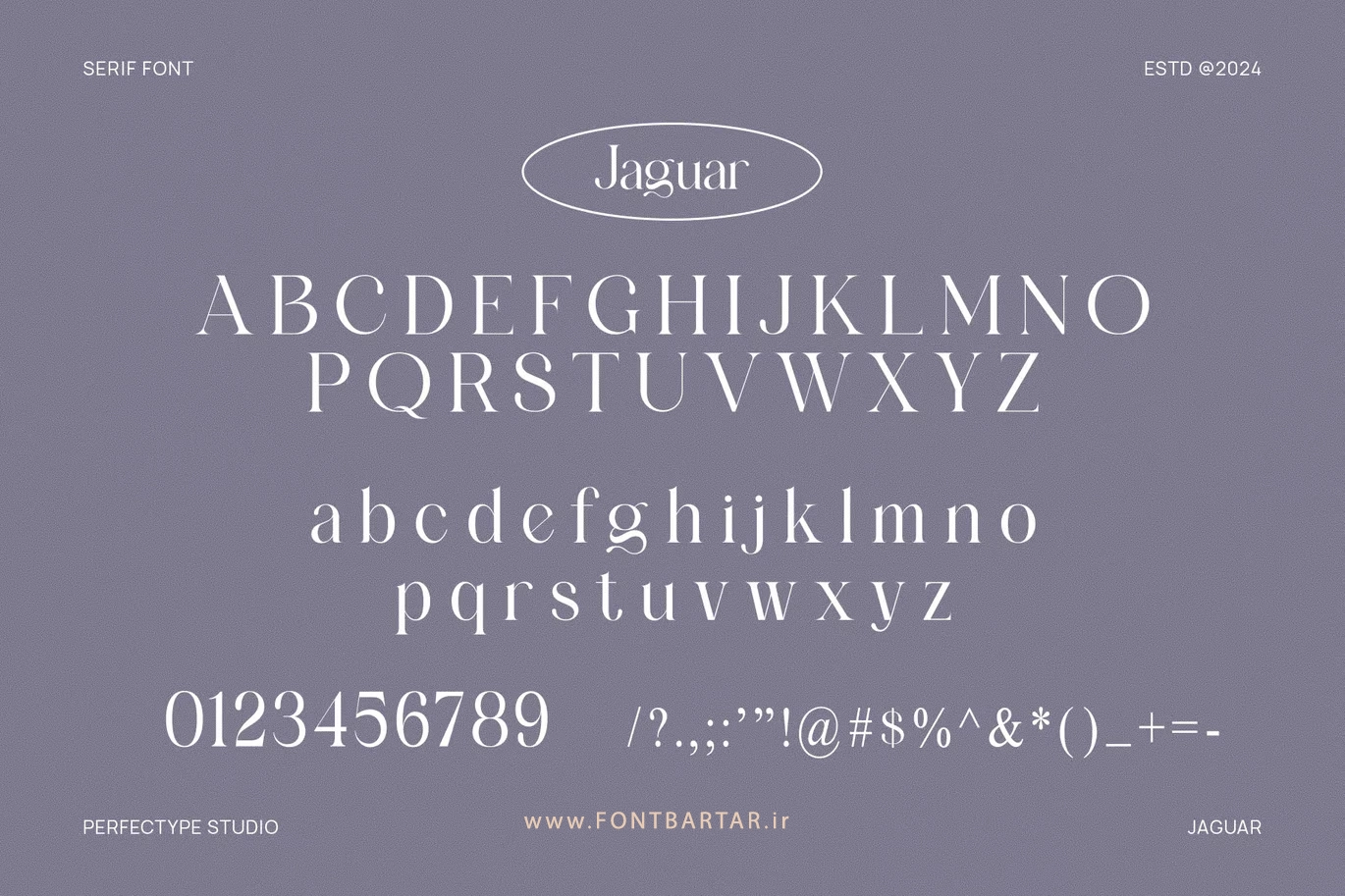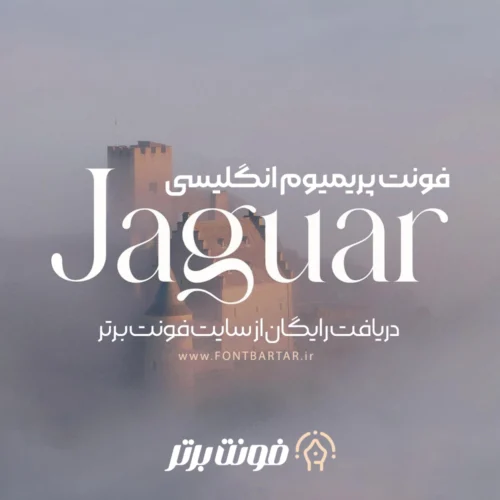
فونت پریمیوم انگلیسی Jaguar یکی از فونتهای خاص و پرطرفدار برای طراحیهای مدرن و لوکس است. این فونت با ترکیب خطوط نرم و انحناهای ظریف، حس شیک و مینیمال را به آثار شما میبخشد. فونت پریمیوم Jaguar اگر به دنبال فونتی هستید که در طراحی پوستر، لوگو، کارت ویزیت، بنر یا محتوای شبکههای اجتماعی جلوهای منحصر به فرد ایجاد کند، Jaguar انتخابی ایدهآل خواهد بود.
ویژگیهای فونت زیبا Jaguar :
- فونت مناسب لوگو طراحی مدرن و مینیمال
- فونت پریمیوم Jaguar مناسب برای برندینگ، طراحی پوستر، تایپوگرافی و وب سایت
- فونت شیک انگلیسی کیفیت بالای حروف و جزئیات ظریف